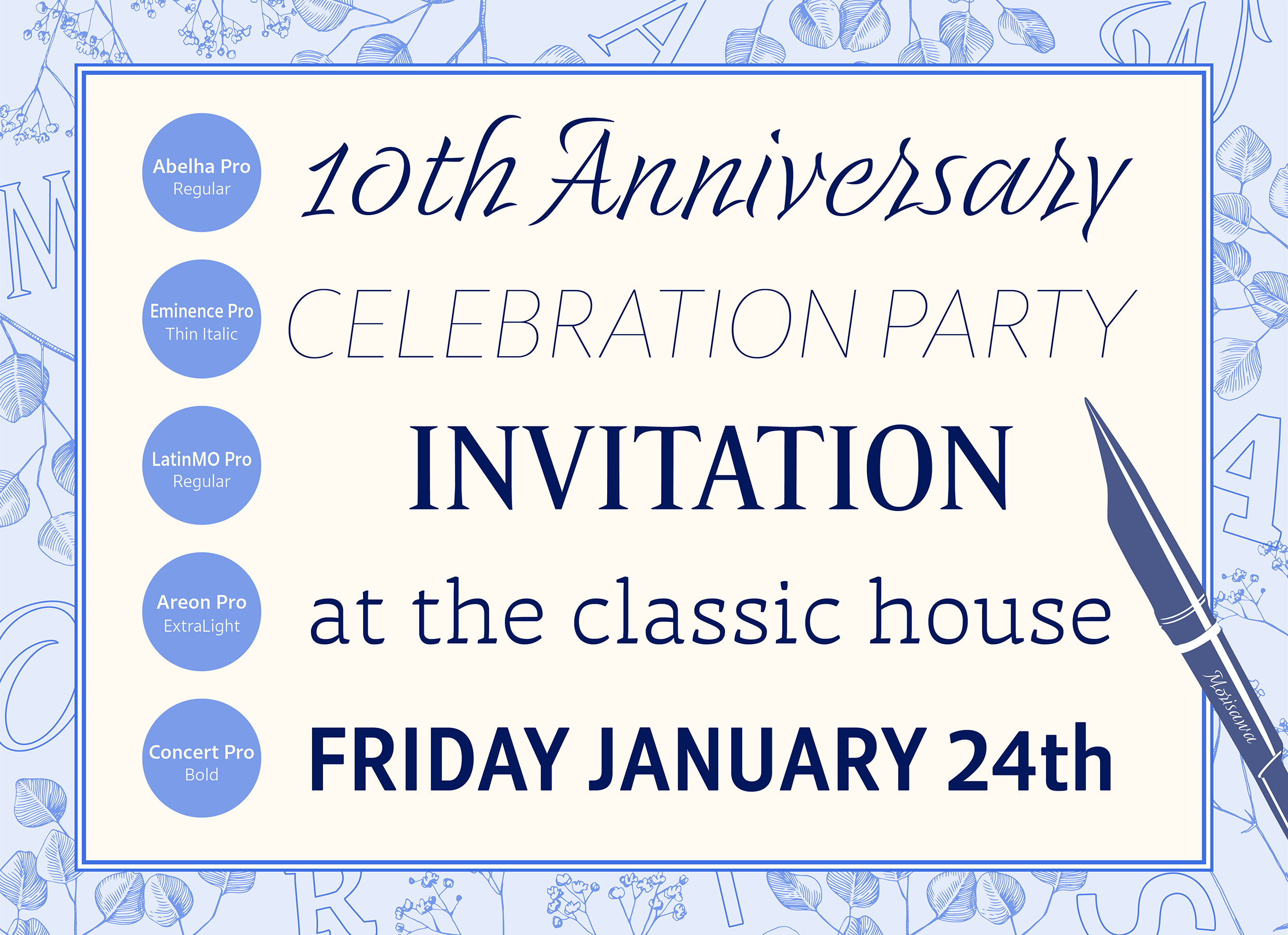
モリサワ 2022年度新書体74ファミリーを発表〜『オーガニック&ディスプレイ』『クラシカル&スタンダード』『Roleスーパーファミリー』『Clarimo UDシリーズ』の4ジャンルで欧文書体を追加〜
株式会社モリサワ(代表取締役社長:森澤彰彦 本社:大阪市浪速区敷津東2-6-25 Tel:06-6649-2151 代表、以下モリサワ)は、2022年秋にリリースする新書体のラインナップ74ファミリーを発表します。本年度は、2022年6月23日付のニュースリリースにてお知らせしている和文デザイン書体などの強化に加え、『オーガニック&ディスプレイ』『クラシカル&スタンダード』『Roleスーパーファミリー』『Clarimo UDシリーズ』の4ジャンルの欧文書体49ファミリーからなる合計74ファミリーを追加します。
目を引く華やかな見出し書体やベーシックな書体、統一感のあるデザインで多くのウエイトが揃う書体までカバーする大幅なアップデートとして、欧文書体の選択肢がぐんと広がり、また上手く活用することでデザインクオリティーにも差をつけられる実力派の書体ラインナップです。近年、日本語だけでなく欧文をはじめとする多言語併記が必要な場面も増えています。モリサワは、今後も欧文書体を充実させることで、欧文を使った豊かなデザインを可能にします。
今回追加する欧文ジャンルは、有機的なデザインが目を引くスタイルや強いインパクトを持つ見出し用途の書体が揃う『オーガニック&ディスプレイ』、上品さを感じさせる伝統的なスタイルやシンプルで汎用性の高い書体が揃う『クラシカル&スタンダード』、世界的書体デザイナーのマシュー・カーター氏をメインデザイナーに迎え開発した、200書体を誇る『Roleスーパーファミリー』、UD新ゴとの併記を目的に開発されたサンセリフ体「Clarimo UD PE」のコンデンス(長体)展開『Clarimo UDシリーズ』の4つです。
ジャンル(1) 有機的かつ現代的なスタイルや見出し用途の強いインパクトを持つ『オーガニック&ディスプレイ』
『オーガニック&ディスプレイ』のジャンルでは、平筆の書風から着想を得た現代風のセリフ体「Areon Pro(アレオン プロ)」や、書簡の筆跡を参考にデザインされたフォーマルな印象のスクリプト体「Abelha Pro(アベーリャ プロ)」などモリサワ主催の書体デザインアワード「タイプデザインコンペティション」で入賞した実力作品のほか、太いマーカーペンで書いた文字の形から着想を得たサンセリフ体「Tapir Pro(タピアー プロ)」など、12ファミリーを追加します。欧文組版や和欧併記でのワンポイント利用などで、紙面に華やかなニュアンスをプラスするラインナップです。
ジャンル(2) 上品さを感じさせる伝統的なスタイルやシンプルで汎用性の高い『クラシカル&スタンダード』
『クラシカル&スタンダード』のジャンルでは、15世紀の活字にインスパイアされて制作されたオールド・ローマン体「Pietro Text Pro(ピエトロ テキスト プロ)」や、オンスクリーンでの利用を想定して制作された、シンプルでややジオメトリックなサンセリフ体「Prelude Pro(プレリュード プロ)」など20ファミリーを追加します。ベーシックな欧文組版をはじめ、和文と組み合わせてご利用いただくことでデザインの幅を広げてくれるようなラインナップです。
ジャンル(3) 200書体ものファミリー展開が魅力の『Roleスーパーファミリー』
アメリカで先行リリースされていた『Role』12ファミリーを新書体として追加します。誠実さと安定感をコアイメージとし、Serif、Sans、Slab、Softの4つのスタイルとText(本文用)、Display(小見出し用)、Banner(大見出し用)の3つのサイズシーンを持つ書体群です。200書体すべてをPro仕様にてご提供します。豊富なスタイルやウエイト展開をもち、統一感のあるコンテンツ制作や、多様な展開を要するコーポレートアイデンティティーの制作などに最適な書体です。
ジャンル(4)『Clarimo UDシリーズ』から「Clarimo UD PE」のコンデンス(長体)展開
「Clarimo UD PE」に、Narrow / Condensed / Extra Condensed / Compressed / Extra Compressed の5段階の長体率のコンデンス書体5ファミリーを追加します。元となる「Clarimo UD PE」は、UD新ゴとの併記を目的に開発されたUDフォントとして、可読性を重視したシンプルで汎用性の高いサンセリフ体です。本シリーズは欧文以外も豊富な言語で展開しているため、書体のデザインを多言語で統一したい場面に活用できるラインナップです。